30 種最佳黑板字體(免費和高級版)
已發表: 2021-08-27為您的下一個項目尋找可愛而古怪的字體? 想讓您的設計具有質樸的手繪外觀嗎? 黑板字體正是您所需要的。
黑板字體是獨一無二的,視覺上很有趣,而且用途廣泛。 無論您是在尋找粗體輪廓字體還是更精緻的字體,您都一定能找到一種黑板字體來融入您的設計。
在本文中,我們將介紹免費和高級網站上提供的 30 種最佳黑板字體。
但首先,讓我們了解一下什麼是黑板字體。
什麼是黑板字體?
黑板字體是旨在模仿黑板上字母樣式的字體。 通常,它們具有顆粒狀的潦草紋理,以賦予它們白堊的外觀。
黑板字體有許多不同的種類,以適應各種美學。
有些是精緻的排版字體,在咖啡館菜單上看起來很棒,而另一些則讓人想起帶有童趣字體的老式黑板。
繼續閱讀以找到適合您項目的完美黑板字體。
最好的免費和高級黑板字體
這裡有 30 種在線可用的最佳黑板字體。 從我們個人最喜歡的開始……
1. Coffee Lab 黑板字體集合——我們的首選
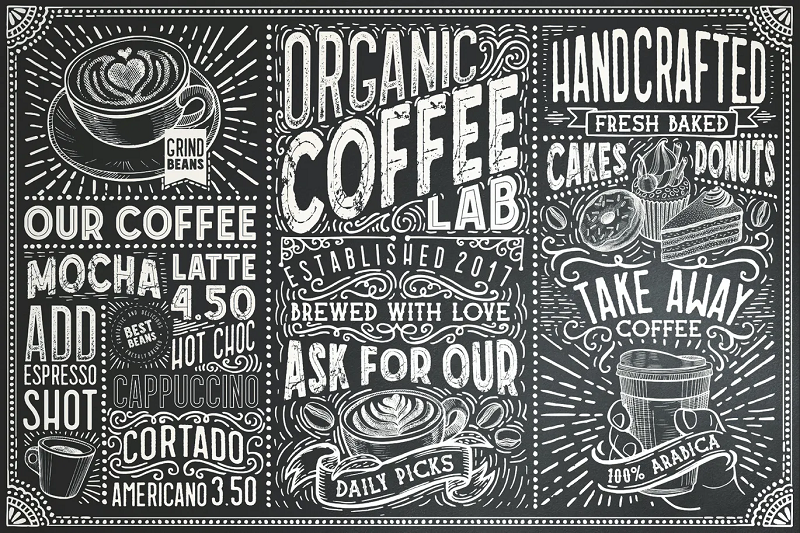
Coffee Lab 字體系列是任何想要一系列酷黑板字體可供選擇的人的完美選擇。
該包包括 15 種不同的樣式,包括內聯、輪廓、復古粗糙和圓形。 作為咖啡館板設計的一部分,或作為海報和日誌設計的一部分,這個系列中的字體看起來很完美。
2.飢餓的粉筆字體
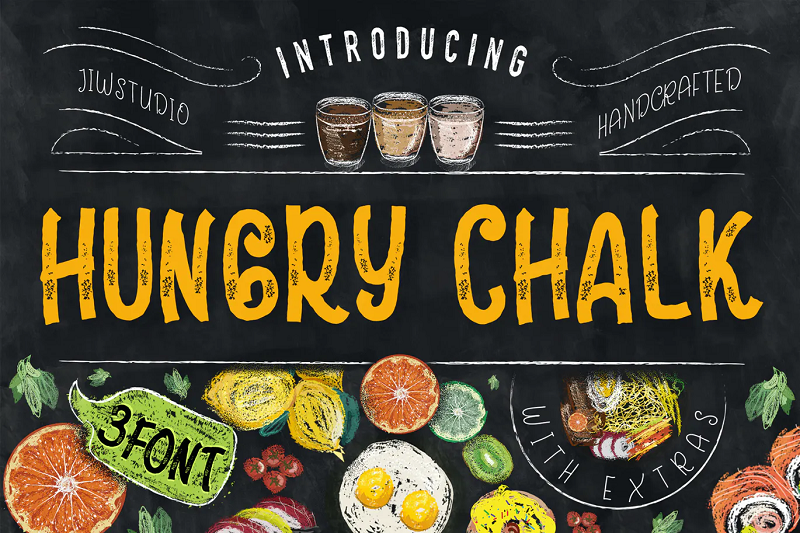
Hungry Chalk 是一種大膽而有趣的黑板字體,非常適合用於標牌和海報。 該字體的靈感來自咖啡店的黑板和菜單。 這種字體的優點在於它非常醒目且易於閱讀。
3.黑板——手工粉筆字體
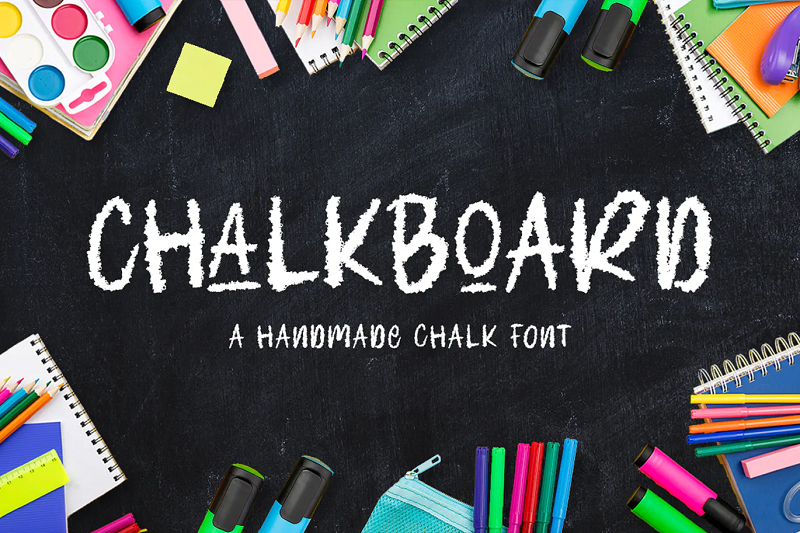
黑板是一種傳統的黑板字體。 這種簡單的手工字體易於閱讀,但非常有趣和時尚。 該字體讓人想起學校的黑板,非常適合用於學校設計或針對兒童的設計。
4.繪圖指南
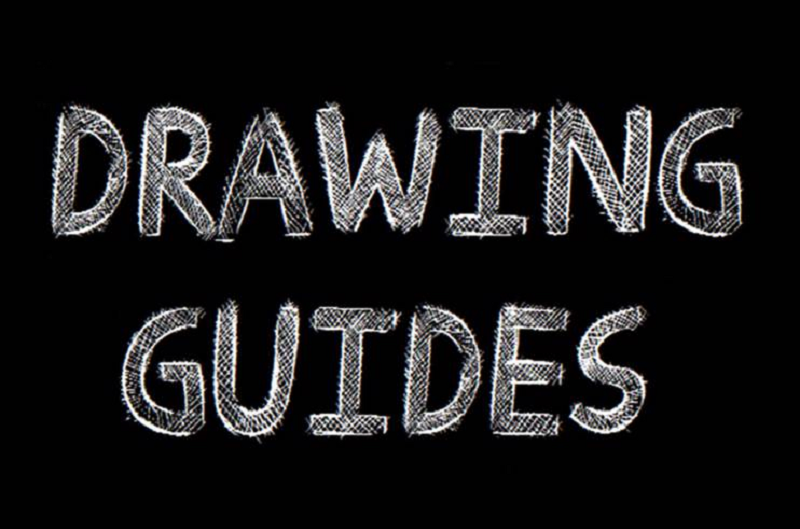
如果您正在尋找一種真正脫穎而出的黑板字體,繪圖指南是完美的選擇。 這種字體粗體且易於閱讀,但仍然具有經典黑板字體的所有元素。 該字體充滿了時尚的交叉影線設計,非常適合為海報或標誌添加一點視覺趣味。
5.粉筆區
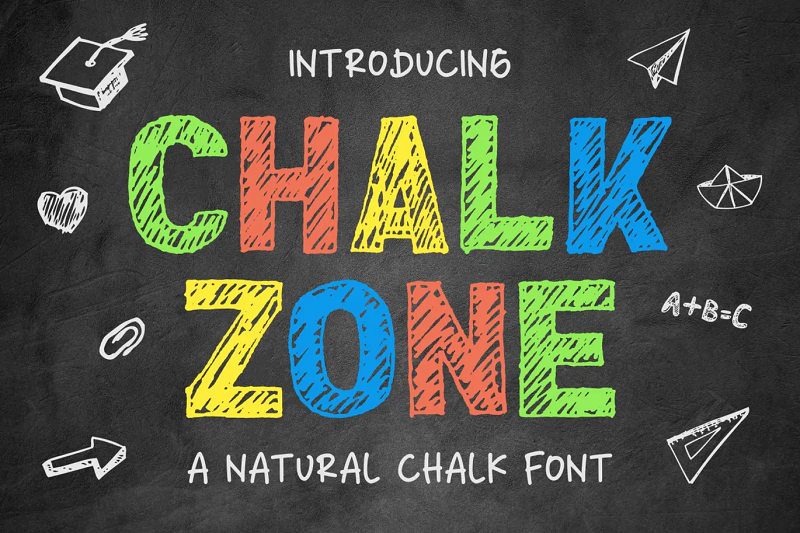
Chalk Zone 是一種俏皮的塊狀字體,非常適合在教室或以兒童為中心的設計中使用。 字體都是大寫的,所以它真的跳出了頁面。 這種黑板字體的顏色或傳統的白色粉筆風格看起來很棒,非常適合各種項目,從菜單板設計到 T 卹。
6.粉筆素描
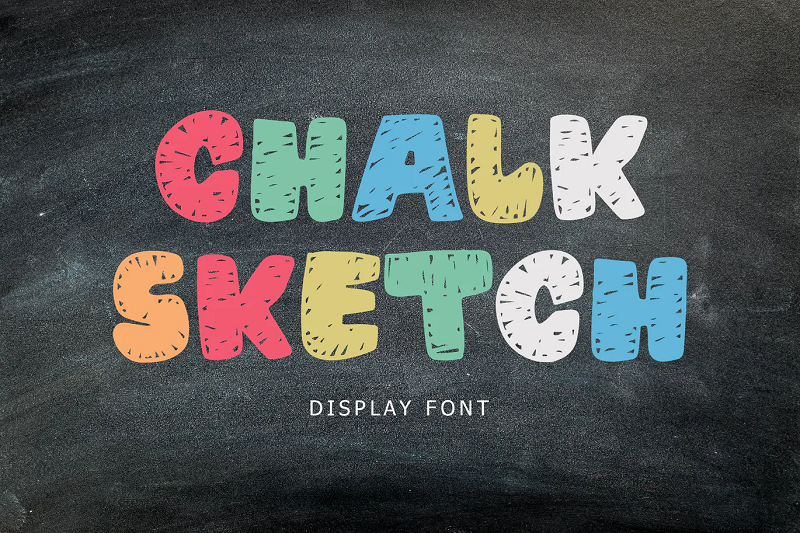
Chalk Sketch 是一種彎曲的塊狀字體。 它非常引人注目且易於閱讀,在 T 卹、馬克杯和其他商品上看起來很棒。 字體包包括大寫字體以及一系列標點符號和字形。
7.白粉筆
White Chalk 是一種非常時尚和經典的粉筆字體。 這種風格的襯線字體是婚禮請柬、家居裝飾品或菜單等高檔設計的完美選擇。 該字體易於閱讀和傳統,使其成為菜單的絕佳選擇。
字體包包括大寫和小寫字符以及數字和標點符號。
8. DeCapoers 黑板字體
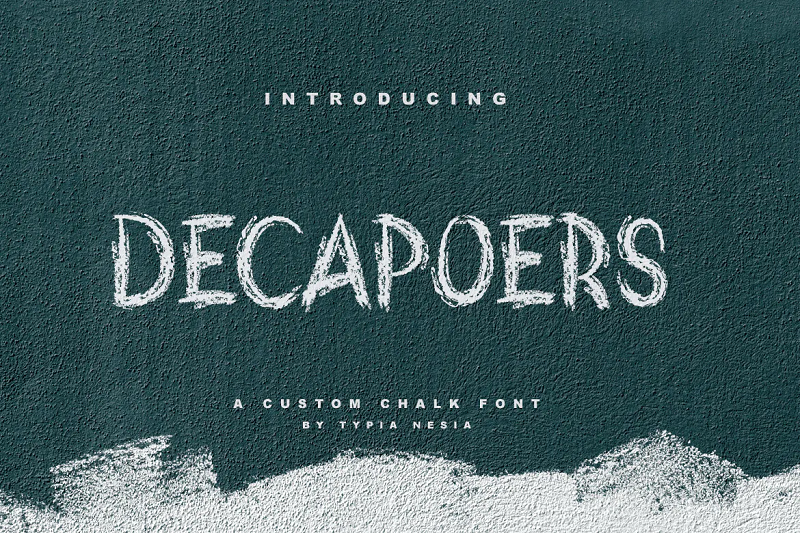
DeCapoers 是一款真正獨特且時尚的字體,適合各種項目。 這種字體真的有一種手寫的感覺,可以幫助增加設計的真實性和個人風格。
這種字體在專輯封面、T 恤上看起來很棒,甚至在 YouTube 視頻和頻道藝術中也能很好地工作。
9.橡皮擦
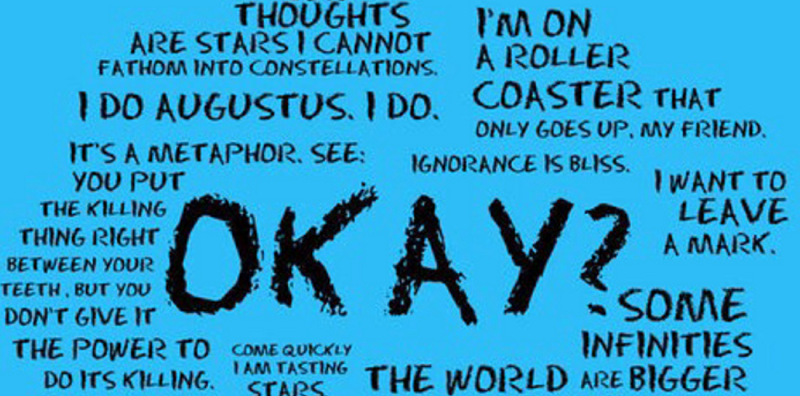
Eraser 是一種邋遢的黑板字體,非常適合具有都市美感的設計。 該字體讓人聯想到塗鴉風格的藝術作品,在 T 恤和其他商品上看起來很棒。 儘管它的風格前衛,但它仍然易於閱讀且非常引人注目。
10.無名字體
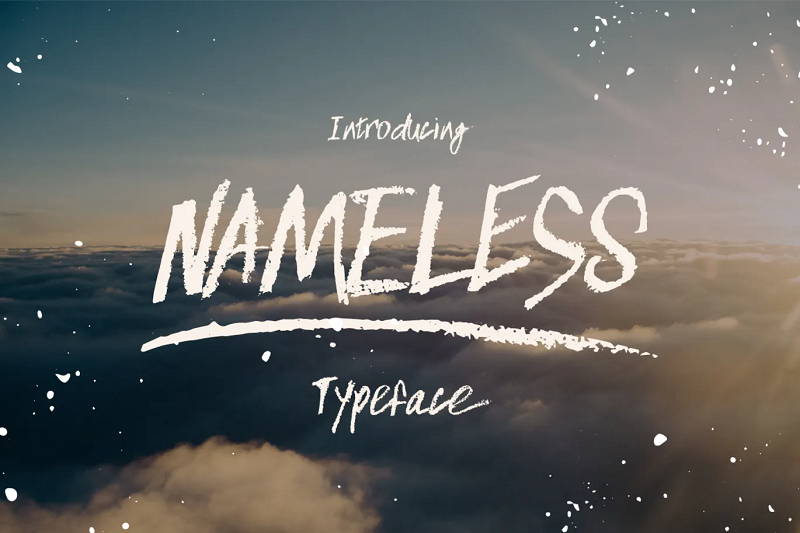
Nameless 是一種手繪粉筆字體,非常適合冒險旅行視頻。 字體包包括大寫和小寫字體,以及字形和標點符號。
此外,該字體還帶有匹配的花體和飛濺,您可以使用它們來創建與字體完美互補的令人敬畏的 grungy 設計。
11. Bellanovie 黑板字體
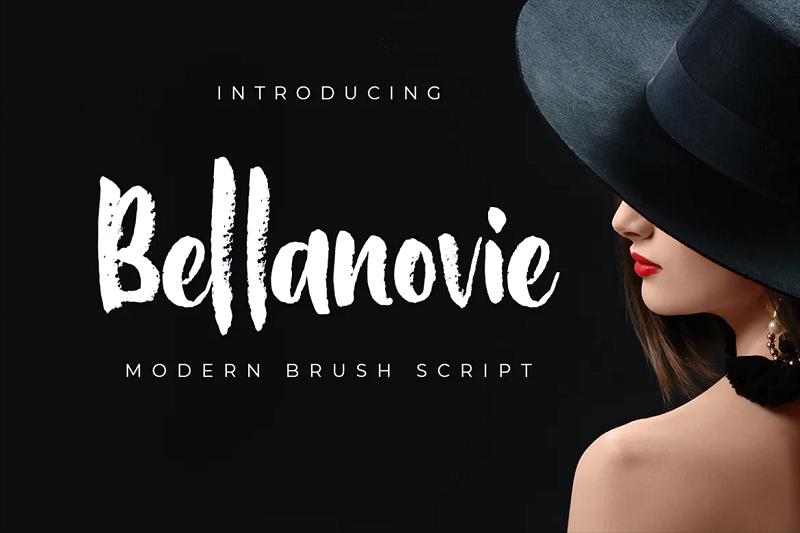
Bellanovie 是一種優雅、女性化的字體,非常適合優雅的設計。 無論您是為美容業務創建黑板標牌還是設計自己的婚禮請柬,這種字體都是完美的。
該字體的設計類似於經典的畫筆字體,但它具有顆粒狀的紋理,給人一種白堊的手寫感。
12.小賣部
Tuck Shop 是一個使用粉筆和實際石板手繪的字體系列。 這個正宗的黑板字體系列非常適合菜單、標牌等。
字體系列包括 3 種樣式; 規則、輪廓和裝飾。 特別是大綱樣式大膽而有影響力,非常適合標誌和標題。
13.哈爾基茲
Chalkiez 是一種清晰、粗體的黑板字體,非常適合用於標誌、海報和標題。 儘管它的靈感來自於黑板風格,但顆粒感非常小,如果您將閱讀的便利性放在首位,這將是一個不錯的選擇。
14.兒童知識字體
Kids Knowledge Font 系列包括五種不同的創意字體,非常適合以兒童為中心的設計。
除此之外,下載還包括一組補充字體的塗鴉剪貼畫。 這個字體系列非常適合需要出色的黑板字體來創建學校資源的教師。
15.你好塗鴉
Hello Scribbles 是一種有趣且活潑的黑板字體,在海報、學校資源等上看起來很棒。 字體下載包括大小寫字母、字形和標點符號。 這是一種很好的字體,可以為您的設計增添一些視覺趣味,同時仍然非常易於閱讀。
16.范德查克字體
Vanderchalk 是一種粗體的手工字體。 它非常時尚且易於閱讀,非常適合在咖啡館和咖啡店使用。 此字體下載不僅包括 Vanderchalk 字體,而且還有一些用於創建古怪黑板設計的額外塗鴉矢量。
17.新娘粉筆字體
為您的婚禮請柬或標誌尋找優雅的黑板字體? 就是這個。 BrideChalk 是一種令人驚嘆的粉筆字體,一定會給您的婚禮帶來更質樸的感覺。
字體包包括 3 種不同風格的 BrideChalk; Script、Serif 和 Sans。 它還包括額外的花朵和邊框,可幫助您創建真正優雅的設計。
18. BiteChalk 字體
BiteChalk 是一種時尚的無襯線黑板字體,幾乎適用於任何項目。 該包包括 4 種不同的樣式; BiteChalk、粗體、正常和苗條。 如果您正在為菜單板尋找完美的字體包,就是這樣。
這不僅是完美的粉筆字體,而且該包還包括一系列粉筆風格的矢量食物圖像,可以幫助提升您的設計。
19. LaChalk 字體
LaChalk 是一種優雅的黑板字體,可以幫助您為設計增添一絲優雅。 該字體的靈感來自咖啡館風格的菜單板,但在從菜單到婚禮請柬的一系列設計中看起來都很棒。
下載包括兩種不同的字體; LaChalk 是一種厚實優雅的粉筆字體,而 Chalks 是一種狹窄的無襯線字體,與 LaChalk 完美搭配。